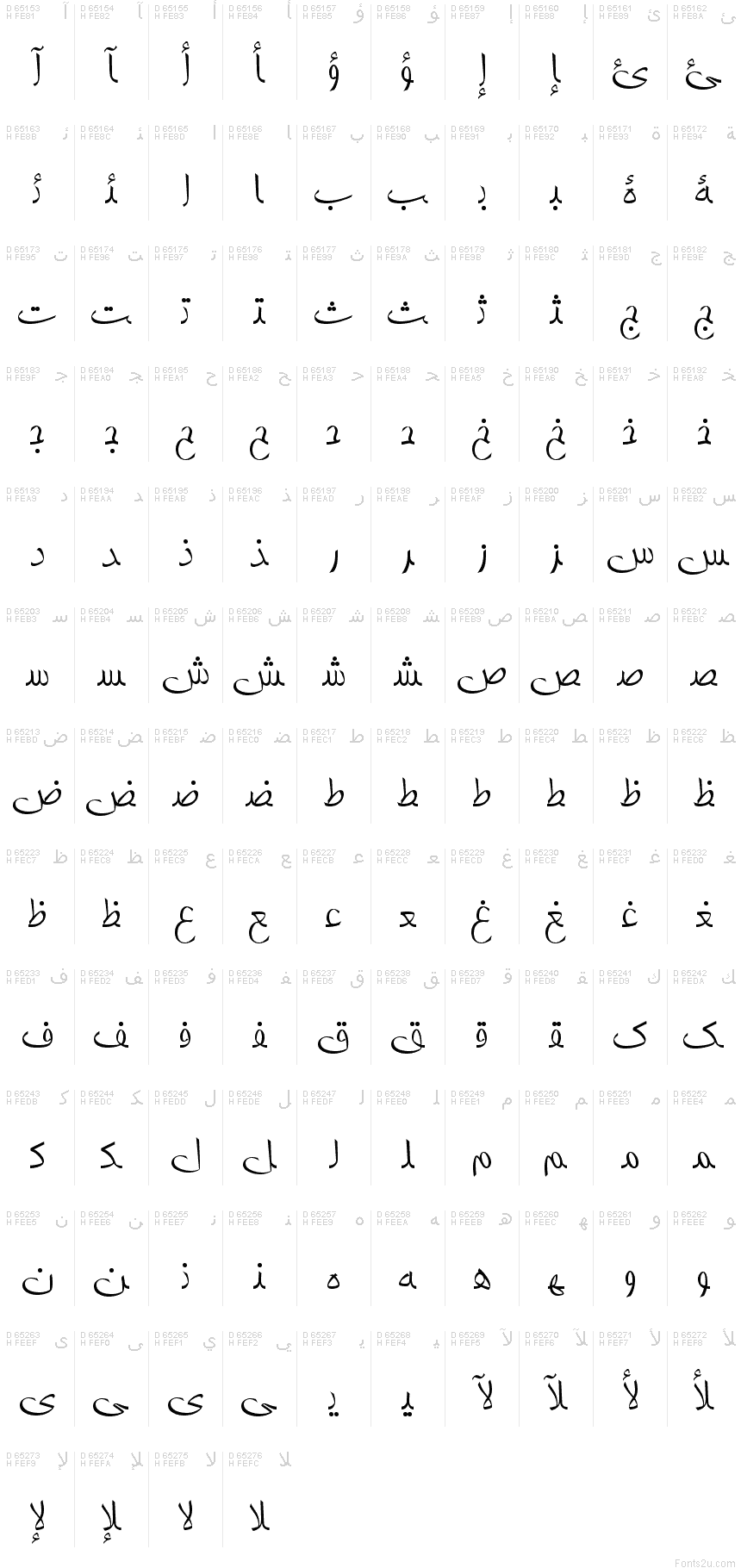
B Tabassom, un carattere display arabo gratuito di Borna Rayaneh, ha uno spirito amichevole e scritto a mano, con lettere arrotondate e connesse che creano un ritmo fluido. Le forme appaiono compatte e morbide anziché formali, conferendo al testo una presenza calda e colloquiale, che invita alla lettura invece di imporsi.
Questo rende questo font gratuito una scelta naturale per manifesti culturali, insegne di librerie o caffè, biglietti d'auguri e brevi titoli su packaging, laddove un tocco arabo delicato è l'ideale. Si presta bene anche per copertine e titoli, poiché il movimento delle lettere connesse rende vivaci e personali anche le parole più brevi.
Mappa dei caratteri di B Tabassom: Presentazione araba forme-B, pagina 1